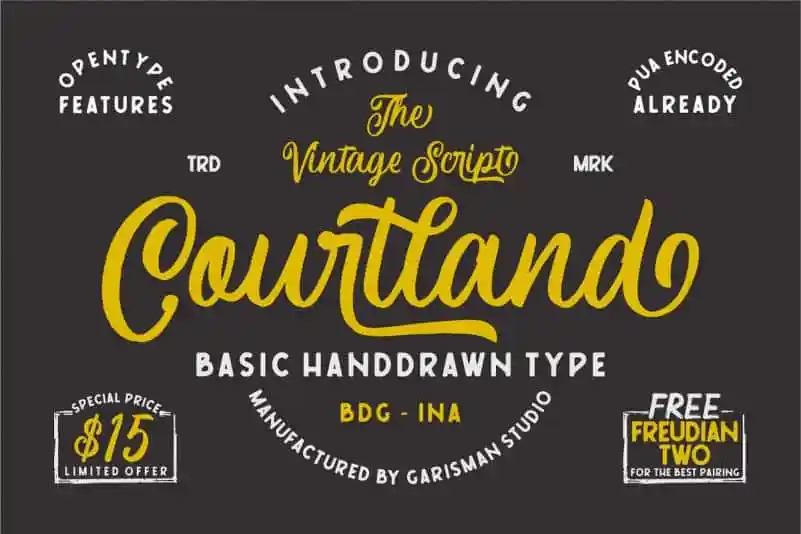
Courtland Handdrawn Font
A Courtland Handdrawn Font é uma nova descoberta para os designers que buscam adicionar um toque único aos seus projetos. Especificamente ideal para criar títulos e logotipos, ela oferece um visual luxuoso e moderno que destacará sua criação. Esta fonte foi criada por Garisman Std, designer responsável pelo design da Courtland Font. O grande mérito desta fonte é o seu estilo antiquado, que se assemelha a uma pintura de arte manuscrita, sem perder a essência contemporânea do design moderno. Ela combina elementos de tipografia serifada e sans-serif de forma harmoniosa para criar um conjunto versátil de opções. Além disso, o detalhe do uso de ligaturas abertas e alternativas estilizadas proporciona uma grande liberdade aos criadores na criação de textos. Um dos recursos mais interessantes da Courtland Handdrawn Font é seu recurso OpenType, que inclui sets estilizados (Stylistic Sets 01 ao 06) em diferentes estilos por letra. Isso oferece uma ampla gama de opções para personalizar o visual da fonte e torná-la ainda mais atraente. Ideal tanto para uso em logotipos vintage quanto em postais, etiquetas, embalagens, headlines e até mesmo camisetas, a Courtland Handdrawn Font é uma escolha perfeita para qualquer designer buscando uma opção única e criativa. Com seu design inspirado por um designer canadense que criou este elegante estilizado fonte vintage, garantirá que cada projeto seja algo único e memorável.